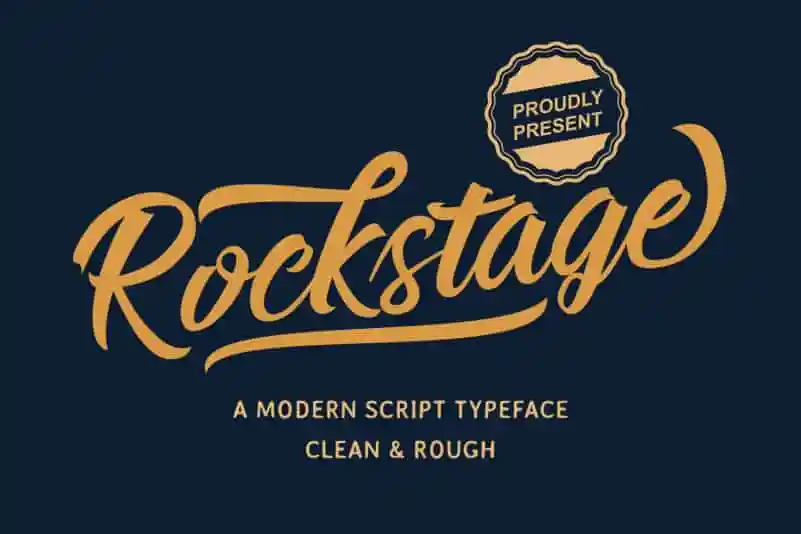
Rockstage Calligraphy Font – Download Grátis
A fonte ‘Rockstage Calligraphy Font’ oferece uma experiência visual encantadora para designers inquietos que buscam dar um toque autêntico e distinto a seus projetos digitais. Ela é perfeita para aqueles momentos especiais como convites de casamento, cartões de agradecimento, frases motivacionais ou cartões de aniversário. Além disso, também se destaca para criar um design forte e memorável em logotipos ou cartões de visita. Seja no formato de uma convidação romântica ou na criação de uma identidade visual única para sua marca, a ‘Rockstage Calligraphy Font’ traz à tona um estilo elegante e autêntico que combina perfeitamente com qualquer projeto gráfico. Com o design delicado e distinto da Mozarella, essa fonte é a escolha certa para dar uma sensação de profundidade e originalidade aos seus designs digitais.